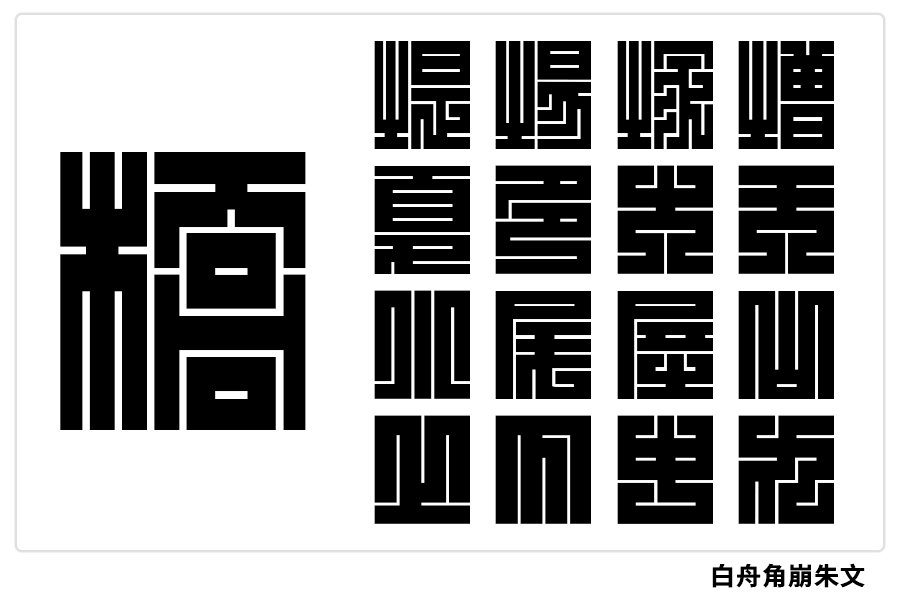
角字(かくじ)又称“腰文字”,与前几种江户字体的风格极大的不同,角字是一种图形艺术字符。它笔划极粗,源于篆体,是由水平线与垂直线组成的字符。字体笔画横平竖直,布白匀称,笔画撑满四边。因为特殊的形状,它不能被用于阅读,而是将文字作为图案所设计。
在正方形这个有限的空间里,将所有文字都封闭起来的图形设计,能让人们感受到日本人对小物件特有的执着。
在江户时期,角字被作为腰部图案、挂装图案和领子装饰等印制在着装上。
简单而深奥的“角字”至今仍被广泛使用于祭典上穿的被称为“半被”或“印半缠(しるしばんてん)”的和服、商标、印章、家纹、招牌设计等。